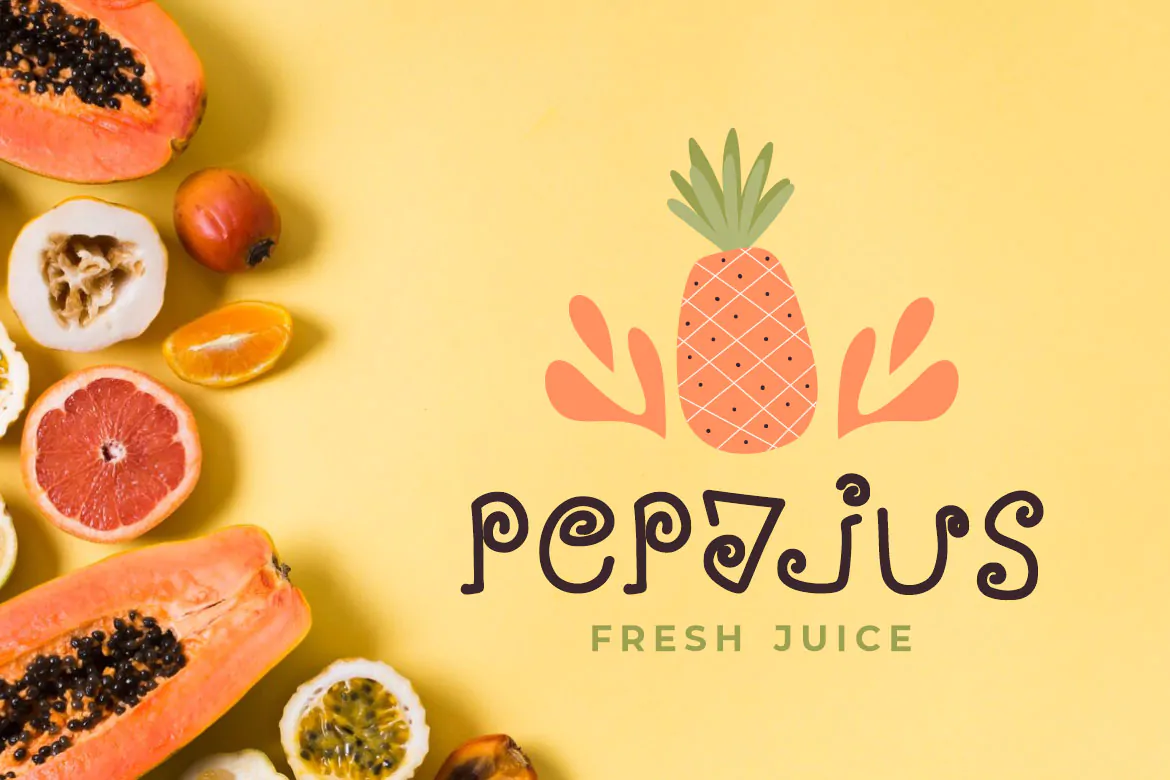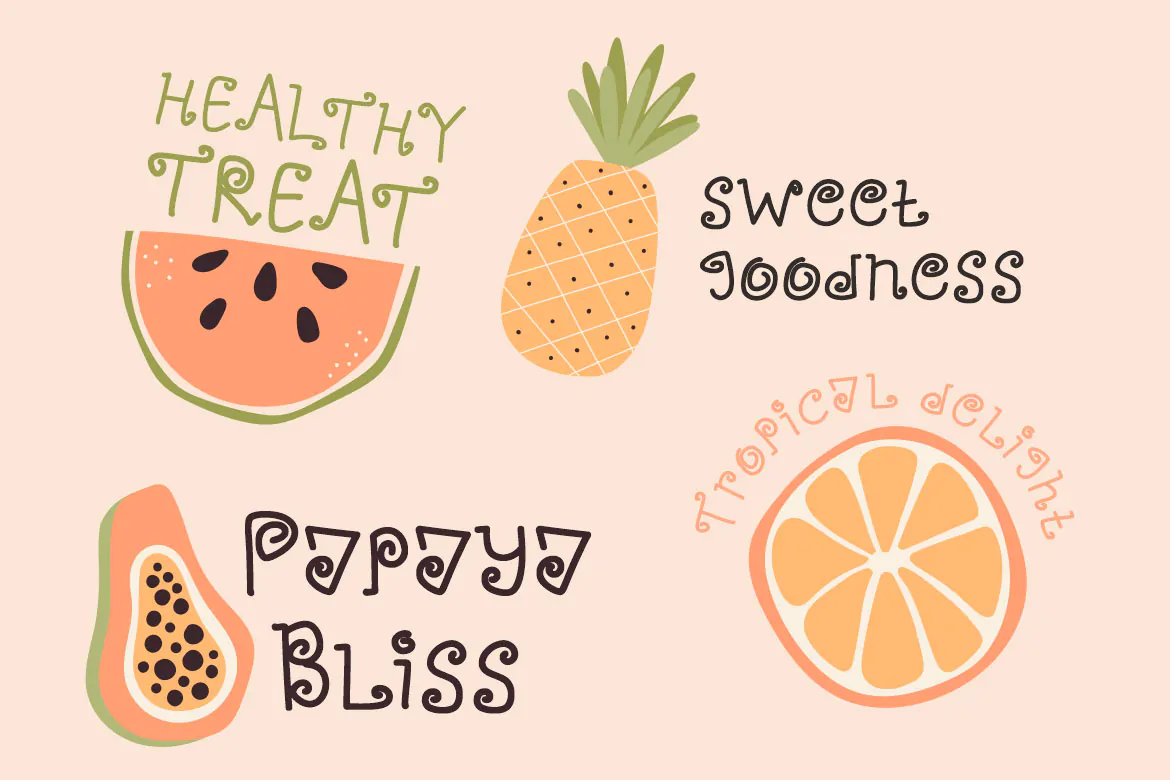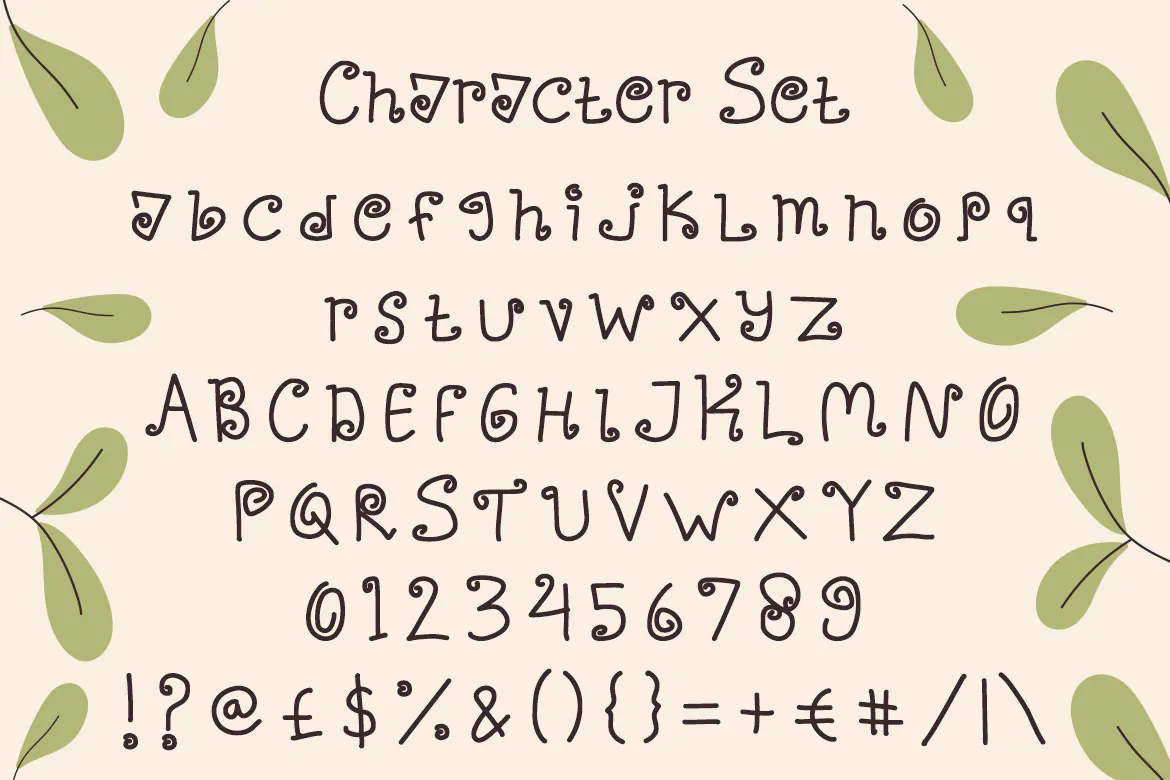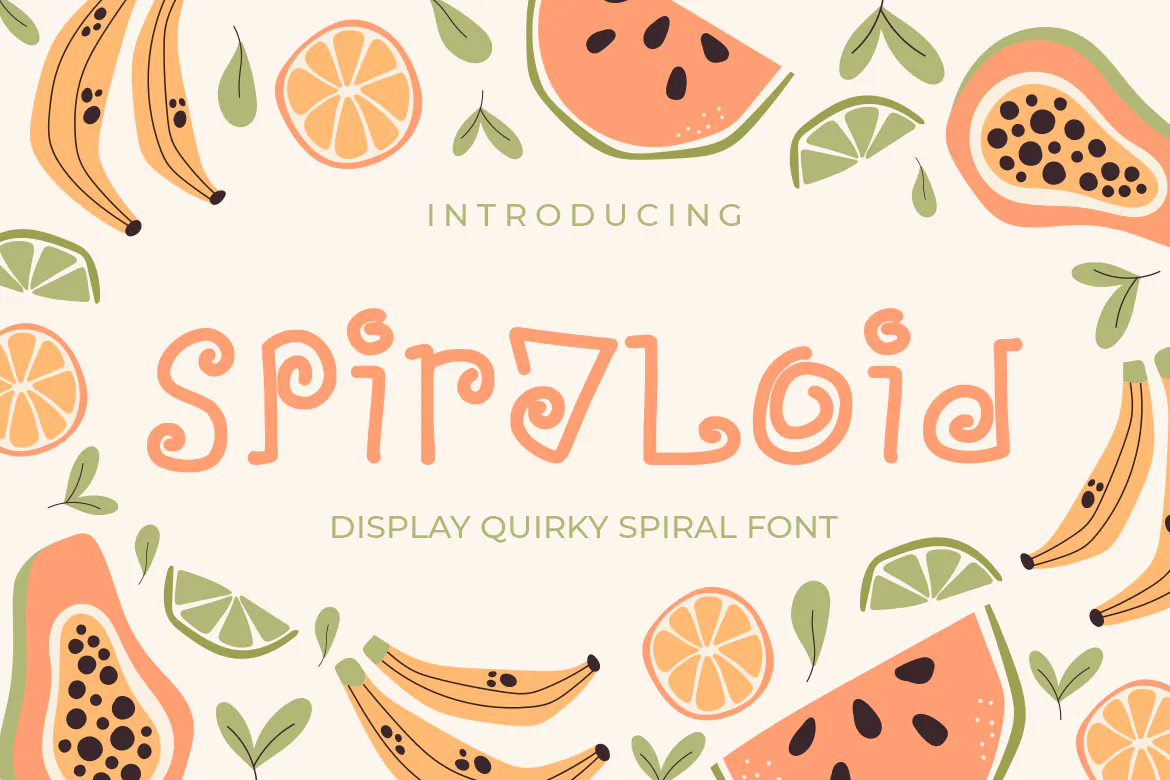
فونت کودکانه مارپیچ
فونت کودکانه مارپیچ یک قلم انگلیسی فوق العاده زیبا است که میتوانید از آن در طرحهای گرافیکی مختلف به خصوص پوسترهای کارتونی و کودکانه استفاده کنید.